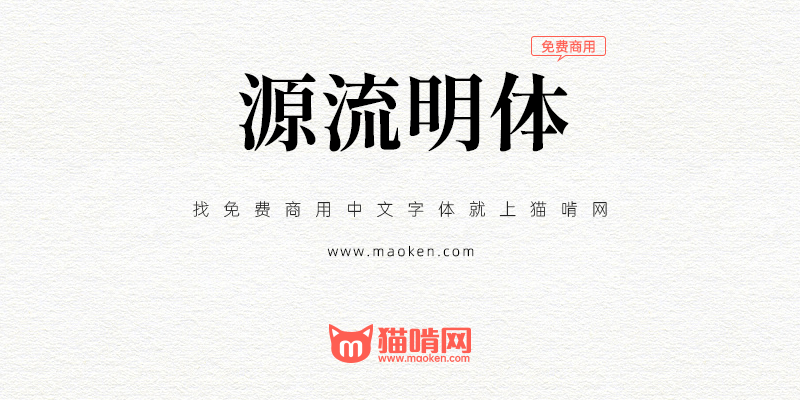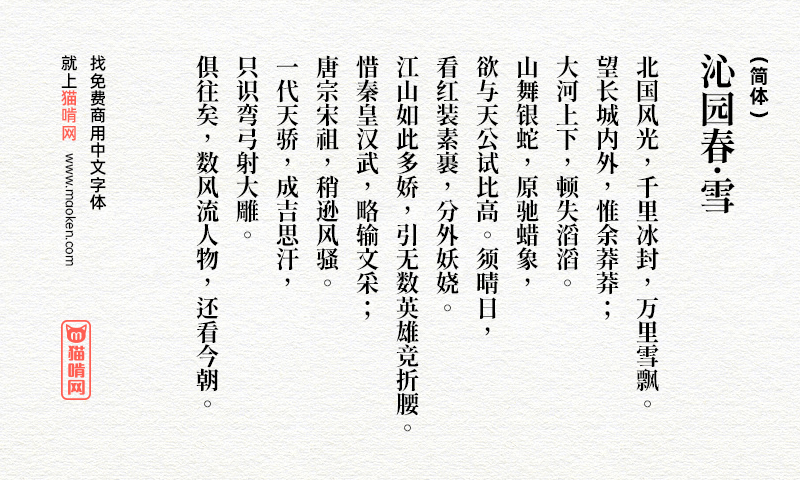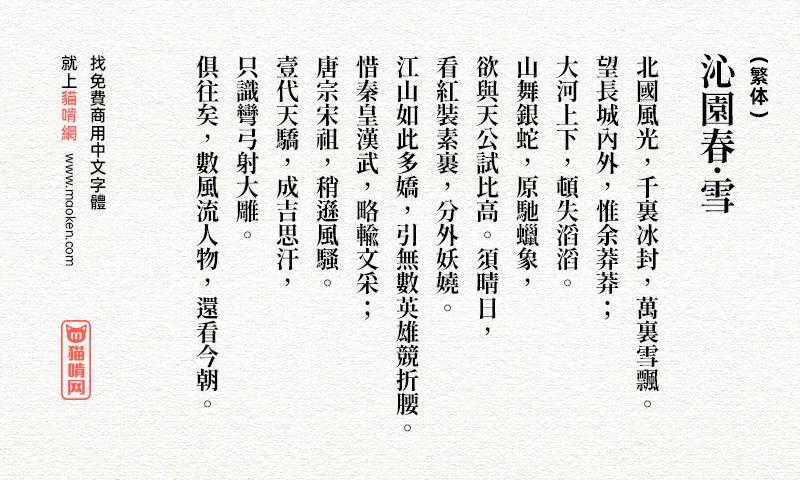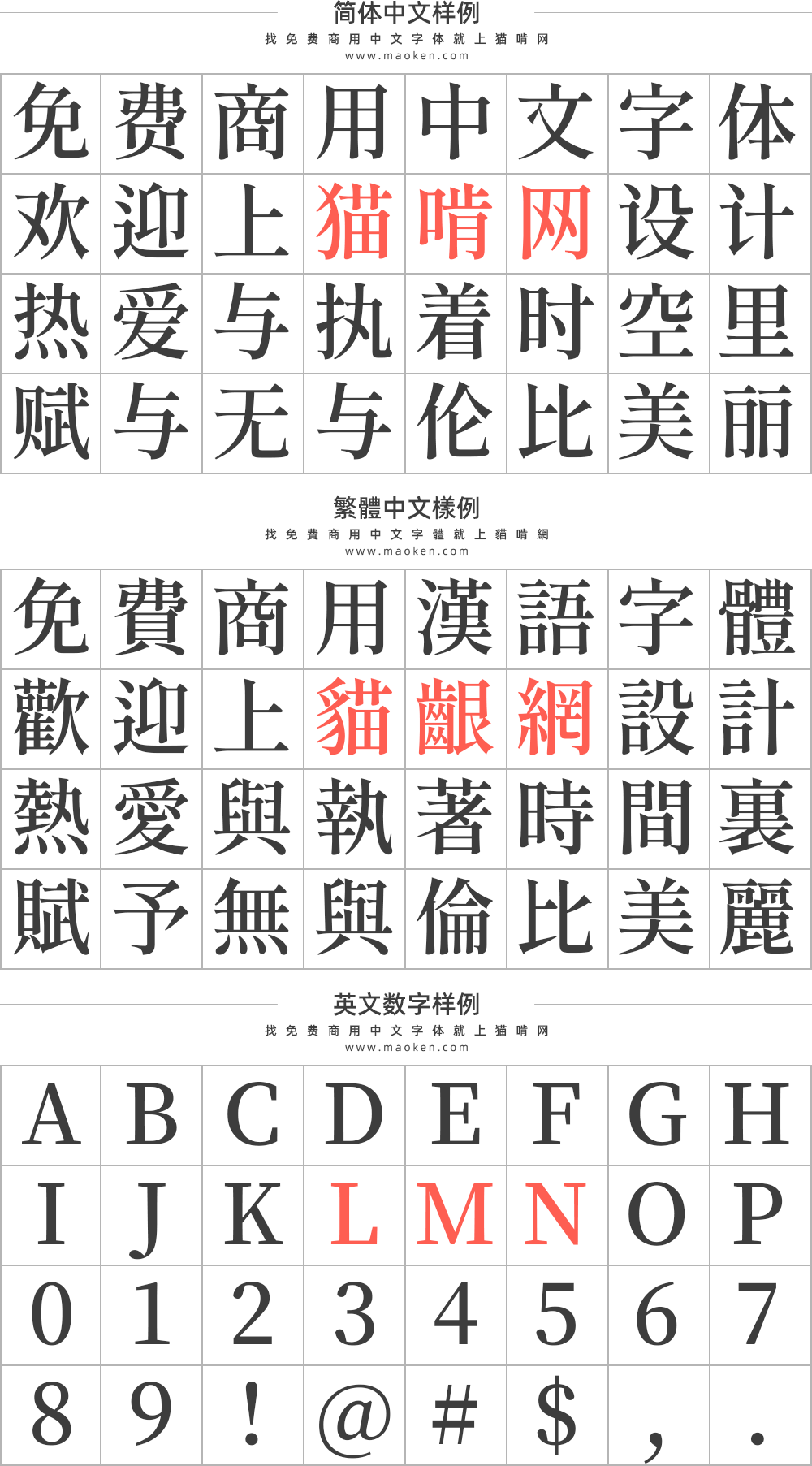
源流明体:笔划带有抑杨顿挫的思源系中文字型
字体作者:But Ko (中国台湾) 字体字重:7个
台湾最活跃的字型社团「字嗨」管理员 But Ko 释出三款改造自思源宋体的繁体中文字型,开放让需要的使用者免费下载!分别为:源样明体、源流明体及源云明体,不过目前仍在公测阶段,不排除未来有大幅更改规格的可能性。无论如何,可以从 GitHub 页面下载使用,将测试结果反映给开发者。
「源流明体」是基于 「 思源宋体 」 的而改造的开放原始码中文字型。汉字宽度稍微压缩,显得比原始的思源宋体要稍微瘦长。 并且在横笔的起笔与竖笔的起笔、收笔处,全都加上粗细变化。 彷彿重现铅字的压印感,文字较有文学感、人文气息。「源流明体」完全重製思源宋体原来所有7个字重。 无论极粗或极细,都能使用思源宋体的古典风格!
Note. 请注意以上改造乃以电脑程序自动进行,未进行任何人工处理,在部分笔画复杂文字可能会有笔画不太一致的情况。
汉字不缺字
「源流明体」保留「思源宋体」所支持之所有汉字(包或日、韩文汉字与简体字),一般会用到的汉字几乎不会有缺字问题。 同时也保留了所有日文假名。(但删除了高达1万字的韩文字,有效降低字体文档的大小)
Ver 2.100(2024/08/22)
• 中文月、丹版,人工重否定百字常用字的写法,让写法世界统一。
• 新增KS X 1001编码范围内的韩文音节2350字与相容字母(输入法显示用)。
• 提供传统粗体模式,让软体的B按钮生效。(实作上是新增X版本,内容与B相同,附属于B版本的ttc文件中一并安装,作为R版本的粗体。otf版本未提供)
Ver 2.000(2024/07/25)
• 中文分为现代通用写法的月版(TW)与传统铅字写法的丹(TC)版,标点改回等宽。
• 日文版分割等宽版本(JP)与比例宽版本(PJP)。
• 新增jf7000当务字集与HKSCS2001汉字。
• 修复一些内的累积问题,如直排时破折号无置中、缺少白话字大写ᴺ。
Ver 1.500(2020/04/11)
• 支持台客语汉字
• 支持台客族语罗马拼音
• 提高注音符号品质,并支持注音直排格式
• 假名与关注类横排时比例宽
• 修改数字2、3、问号为较习惯的形式
Ver 1.300(2018/09/24)
• 修改部分KR版本不理想的文字对应,并统一各自文字的部件。
• 字型风格更加精致化。(三角形椭圆更圆一点。本来只有竖笔有的起笔加强,撇画也加上了。)
Ver 1.200(2018/08/19)
• 解决Word等环境直排时标点符号无法正常旋转的问题。(Word 2007 / Word 2016测试成功。转成PDF也正常。)
这个字体里人类的“类”字是错误的,打成了“米➕犬”了
• 异体字,并没有错
断笔是没错,但是那个竖划右上角的装饰角没去掉 等到全部笔划组合在一起的时候 那个装饰角很不舒服。你们自己打出来那个字看下就知道我说的是什么了。
今天第一次用就发现了字体的BUG,”市”字中间的竖划依然带有装饰角 跟横划以及上面的点 交叉在一起右下角多了个黑点(装饰角)很别扭。所有字重这个问题都在,字重越重越明显。对比原版思源宋”市”字中间竖划没有装饰角,没问题。另外这个字体不是大陆简化字写法,使用范围多少会有点受限制。
• 不是 bug,你自己也说了字体本身就不是大陆规范写法。这字体里的大多数字形都来自于日、韩版的思源宋体,而日、韩版的思源宋体里「市」字的字形就是这样的,是符合对应地区标准的字形。
• 日韩的标准印刷字形中「市」的第一笔是直点,为了与「巿」(U+5DFF,fú)区分,「市」就在「亠」与「巾」中间做了断笔。而中国大陆的印刷新字形是按照楷书写法把直点改成顿点,能与「巿」区分开自然就不需要断笔了。